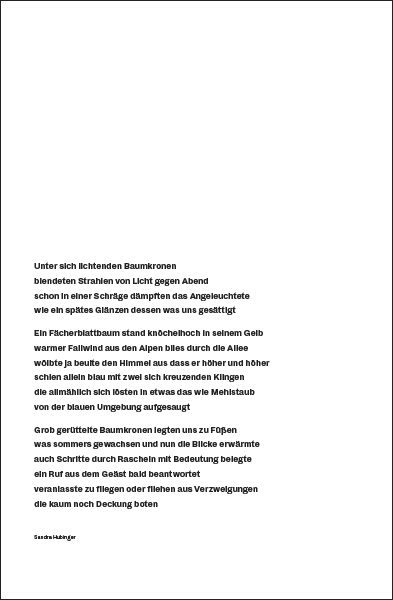
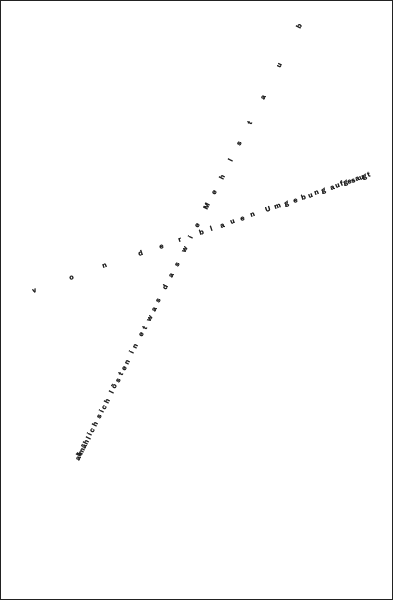
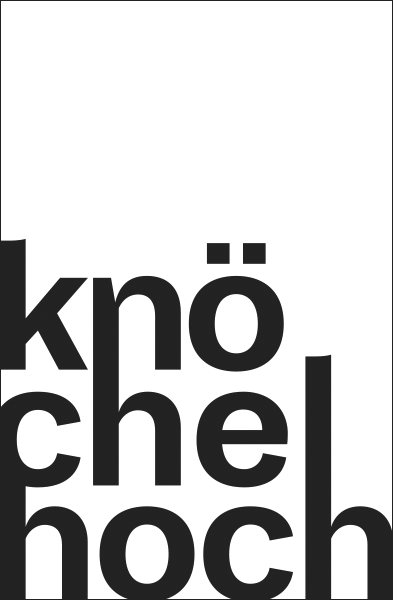
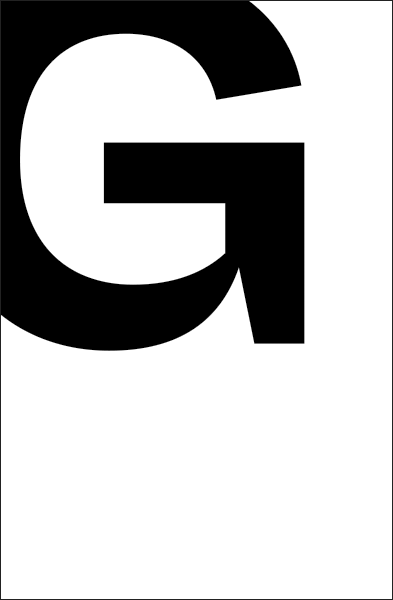
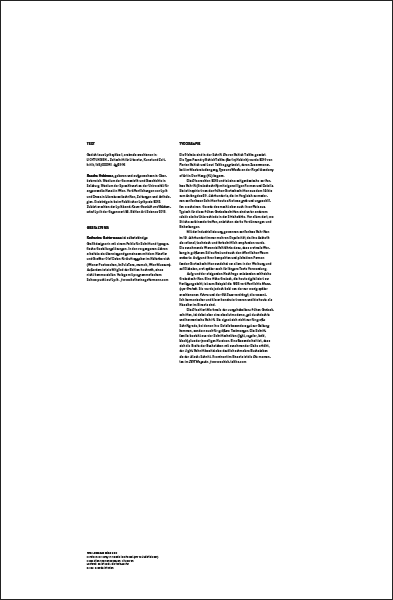
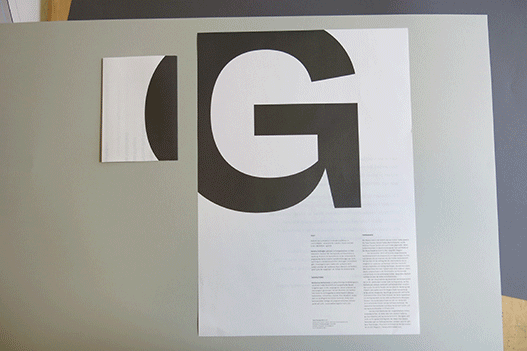
Text
Gedicht aus Lyrikzyklus I, erstmals erschienen in: Lichtungen – Zeitschrift für Literatur, Kunst und Zeitkritik, 146/XXXVII. Jg/2016. Sandra Hubinger, geboren und aufgewachsen in Oberösterreich. Studium der Germanistik und Geschichte in Salzburg. Studium der Sprachkunst an der Universität für angewandte Kunst in Wien. Veröffentlichungen von Lyrik und Prosa in Literaturzeitschriften, Zeitungen und Anthologien. Preisträgerin beim Feldkircher Lyrikpreis 2013. Zuletzt erschien der Lyrikband: Kaum Gewicht und Rückenwind. Lyrik der Gegenwart 56. Edition Art Science 2016.
Typografie
Die Plakate sind in der Schrift Dia von Schick Toikka gesetzt. Die Type Foundry Schick Toikka (Berlin/Helsinki) wurde 2010 von Florian Schick und Lauri Toikka gegründet, deren Zusammenarbeit im Masterstudiengang Type and Media an der Royal Academy of Art in Den Haag (NL) begann.
Die Dia erschien 2015 und ist eine zeitgenössische serifenlose Schrift (Groteskschrift) mit eigenwilligen Formen und Details. Sie ist inspiriert von den frühen Groteskschriften aus dem 19. bis zum Anfang des 20. Jahrhunderts, die im Vergleich zu modernen serifenlosen Schriften heute oft etwas grob und ungeschliffen erscheinen. Gerade das macht aber auch ihren Reiz aus. Typisch für diese frühen Groteskschriften sind unter anderem relativ starke Unterschiede in der Strichstärke. Vor allem dort, wo Striche aufeinandertreffen, entstehen starke Verdünnungen und Einkerbungen.
Mit der Industrialisierung gewannen serifenlose Schriften im 19. Jahrhundert immer mehr an Popularität, da ihre Ästhetik als rational, technisch und fortschrittlich empfunden wurde. Die zunehmende Warenvielfalt führte dazu, dass erstmals Werbung in größerem Stil auftrat und auch den öffentlichen Raum eroberte. Aufgrund ihrer kompakten und plakativen Formen fanden Groteskschriften zunächst vor allem in der Werbung und auf Plakaten, erst später auch für längere Texte Verwendung.
Aufgrund der steigenden Nachfrage entstanden zahlreiche Groteskschriften. Eine frühe Grotesk, die heute digitalisiert zur Verfügung steht, ist zum Beispiel die 1926 veröffentlichte Monotype Grotesk. Sie wurde jedoch bald von der nur wenig später erschienenen Futura und der Gill Sans verdrängt, die wesentlich harmonischer und klarer konstruiert waren und bis heute als Klassiker im Einsatz sind.
Die Dia zitiert Merkmale der »ungehobelten« frühen Groteskschriften, ist dabei aber eine absolut moderne, gut durchdachte und harmonische Schrift. Sie eignet sich nicht nur für große Schriftgrade, bei denen ihre Details besonders gut zur Geltung kommen, sondern auch für größere Textmengen. Die Schriftfamilie besteht aus vier Schriftschnitten (light, regular, bold, black) plus der jeweiligen Kursiven. Eine Besonderheit ist, dass sich die Breite der Buchstaben mit zunehmender Dicke erhöht, der ›light‹ Schnitt besitzt also deutlich schmalere Buchstaben als der ›black‹ Schnitt. Prominent im Einsatz ist die Dia momentan im Zeit Magazin. www.schick-toikka.com
Gestaltung
Katharina Gattermann ist selbstständige Grafikdesignerin mit einem Faible für Schrift und typografische Gestaltungslösungen. In den vergangenen Jahren arbeitete sie überwiegend gemeinsam mit dem Künstler und Grafiker Olaf Osten für Auftraggeber im Kulturbereich (Wiener Festwochen, ImPulsTanz, mumok, Wien Museum). Außerdem ist sie Mitglied der Edition hochroth, eines nicht kommerziellen Verlags mit programmatischem Schwerpunkt auf Lyrik. www.katharinagattermann.com